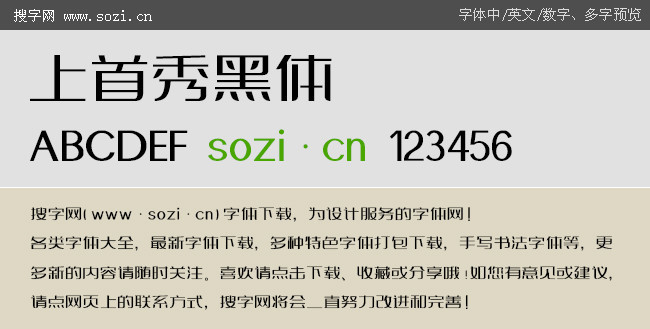
上首秀黑體
搜字網(wǎng)給大家提供一款上首秀黑體中文字體下載,上首秀黑體,整體特征方正穩(wěn)重,筆畫方中帶圓。字體右下角轉(zhuǎn)角處作圓角處理,整體結(jié)構(gòu)剛中帶柔,干凈灑脫,同時(shí)洋溢著成熟、穩(wěn)重、又不缺泛嚴(yán)謹(jǐn)?shù)娘L(fēng)格,適用于戶外廣告、標(biāo)準(zhǔn)字體搭配、金融醫(yī)療、服裝、等行業(yè)。